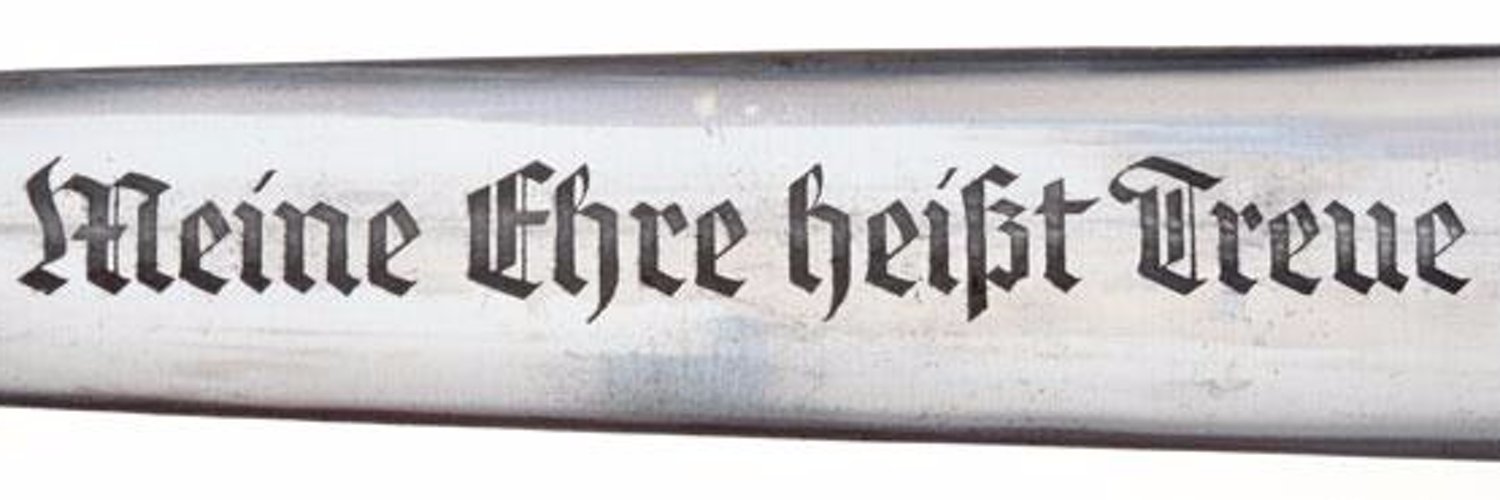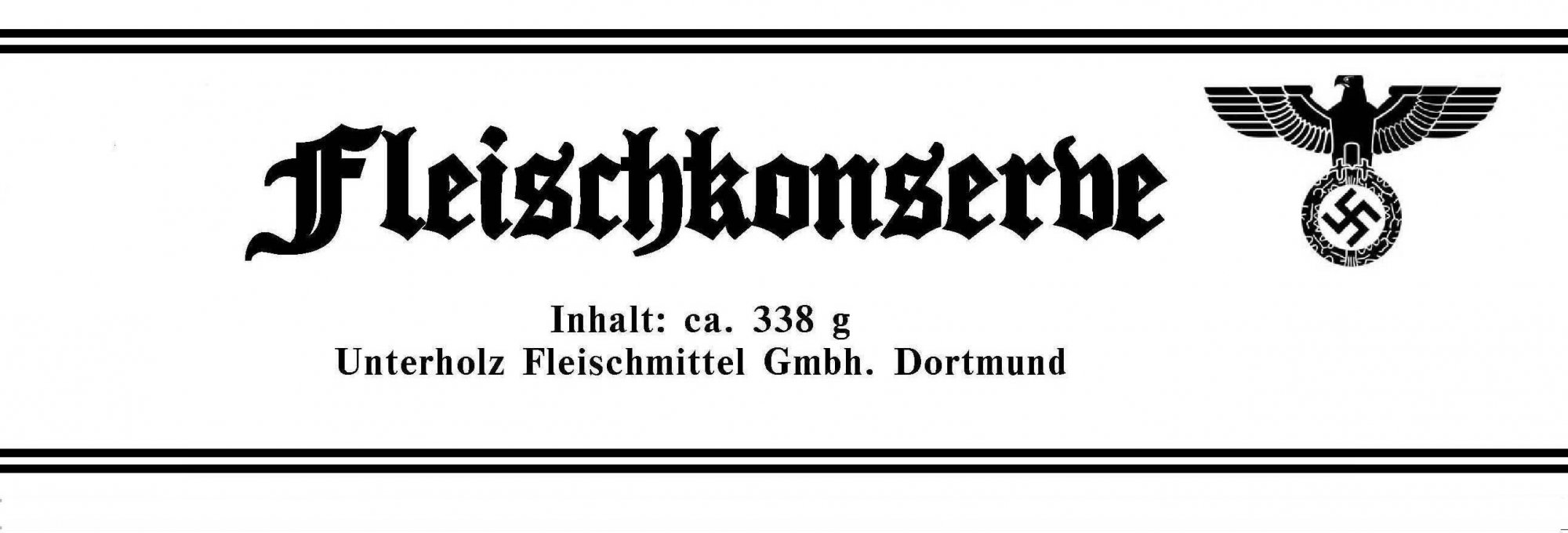
В этот день ровно 70 лет назад — в 1941 году — в Германии было запрещено использовать готический шрифт. Всё — делопроизводство, издательская деятельность и даже частная переписка были переведены на привычный и обычный латинский алфавит. Готическое письмо — или «фрактура» — это такой характерный стиль начетания латинских букв — сплошь изломанные линии, их еще называют «черты и резы». Непривычно для неподготовленного читателя. Очень трудно прочесть. Так что, в школах Германии готическое письмо всегда преподавали как отдельный предмет. Кстати, и это было отменено. Подробности — на радио «Вести ФМ».
На первый взгляд, может показаться, что это какая-то мелочевка, — деталь на фоне угрожающих событий лета 1941 года. Но у тоталитарных диктаторских режима случайных деталей и ходов не бывает. С какой стати нацистам было отказываться от символа национальной культуры? Тем более, что в 1933 году «готику» объявили проявлением истинно арийского духа.
Недаром, в своих агентурных сообщениях на это обратили внимание все британские и советские разведчики, цитируя добытый ими негласный циркуляр Мартина Бормана: «Рассматривать готический шрифт как немецкий — неправильно. В действительности, он состоит из швабских еврейских литер, то есть букв. Так же, как в поздние времена евреи захватили газеты, так в период становления книгопечатания они взяли в свои руки типографии.Фюрер приказал считать латинский шрифт — «нормальным» шрифтом и впредь только он должен использоваться при составлении служебных удостоверений, документов, изготовления вывесок, дорожных знаков и транспарантов…».
Но дело не в том, что нацисты неожиданно репрессировали готический алфавит, заподозрив его в еврейском происхождении. Упомянутые нами разведчики расценили это решение как в «шаг нацистов навстречу» будущим рабам Третьего Рейха.
Объявления, указатели на дорогах — все должно быть адаптировано и доступно для понимания жителей уже оккупированной немцами Европы. И тем, кому эту участь еще предстоит разделить.
В общем, при внимательном прочтении, отмена готики была воспринята как сигнал дальнейшей агрессии Германии.
Шрифт Шиллера и Гёте | Журнал ПАРТНЕР
На протяжении пяти веков им пользовались писатели и ученые, министры и домохозяйки. Возник он на Баварской земле, а затем именно это ему было поставлено в вину. И тайным циркуляром был наложен строжайший запрет на его использование. Сегодня он постепенно возвращается, и события последнего месяца, о которых мы расскажем в конце статьи, заставляют нас вспомнить, как всё происходило.
Немецкая энциклопедия по поводу готического шрифта Frakturschrift, или Fraktur, пишет, что он создан в XVI веке и ему с тех пор отдавали предпочтение (наряду с античными формами шрифтов) не только в Германии, но и в Литве, Чехии, Швеции и Финляндии.
Откуда появился термин «нормальный шрифт» и почему именно в 1941 году произошел такой неожиданный «переворот» в области использования шрифтов?! Энциклопедия Брокгауза, изданная в 1992 году, на эти вопросы ответа не дает.
Оказывается, готический шрифт был официально запрещен в соответствии с циркуляром от 3 января 1941 года № S6/334, подписанным небезызвестным Мартином Борманом. Вот его полный текст (в переводе автора):
«Циркуляр – не для публикации.
По поручению Фюрера сообщаю для всеобщего сведения:
Так называемый готический шрифт рассматривать и называть одним из немецких шрифтов неверно. В действительности так называемый немецкий шрифт состоит из швабахских еврейских букв (в оригинале – Schwabacher-Judenletter – В.Ф.). Точно так же, как позже этот шрифт вошел в употребление в газетах, так как был внедрен в типографии и использован в книгопечатании евреями, живущими в стране. Отсюда и происходит столь широкое распространение швабахских еврейских букв в Германии.
Недавно Фюрер в разговоре с имперским советником господином Аманном и господином Адольфом Мюллером, руководителем типографии, решили, что в дальнейшем нормальным шрифтом следует считать антиква (в оригинале – Antiqua-Schrift – В.Ф.). Следует решительно всю печатную продукцию перевести на этот шрифт. Быстро, как только это возможно, следует перевести на новый шрифт обучение в сельских и народных школах.
Швабахские еврейские буквы в административных учреждениях не применять.
Любые письменные распоряжения государственных чиновников, название улиц и тому подобное следует выполнять только указанным выше нормальным шрифтом.
По распоряжению Фюрера господин Аманн должен перевести на новый шрифт каждую газету и журнал, особенно те, которые распространяются за пределами Германии.
Борман»
Особый курьез заключается в том, что это распоряжение Бормана было напечатано именно тем самым «еврейским» шрифтом, который запрещалось впредь употреблять!
Подтверждения приведенному выше обоснованию заместителя Гитлера по национал-социалистической партии мы найти не смогли. То, что шрифт был изобретен евреями, живущими в городке Швабах (Schwabach), что южнее Нюрнберга, представляется маловероятным. Во-первых, нет письменных подтверждений существования в первой половине XVI века в этом городе еврейской общины. Даже в начале XX века численность еврейского населения Швабаха была менее 100 человек. Во-вторых, в этом городе во времена, о которых идет речь, не было ни мастеров по отливке букв, ни типографий.
Однако следует проводить различие между годами, предшествовавшими 1933 году, и 12 годами нацистского господства. Сначала НСДАП пыталась казаться обоснованной и близкой людям, что часто приводило к грубым, «деревянным» конструкциям с использованием различных типов фрактур и швабахеров (которые также использовались другими партиями).Однако можно найти и примеры использования шрифтов без засечек. С переменным успехом наборщики и графические дизайнеры в Третьем рейхе свободно играли со всем набором шрифтов. В то время как плакат для «Великой немецкой художественной выставки», например, был выполнен в золотом цвете, заглавными буквами и по центру Antiqua, для надписи регионального спортивного мероприятия можно было использовать шрифт черных букв. Точно так же «ценность» продукта часто определяла осторожность, с которой тип или типы были выбраны и применены.